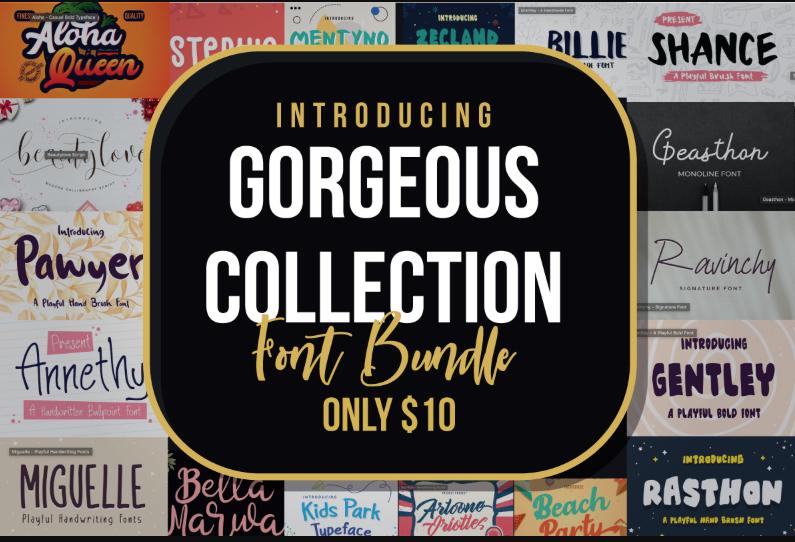
[Сreativefabrica] Gorgeous Collection Font Bundle (Ian Mikraz)
В этом пакете шрифтов вы получите 100 великолепных, профессиональных шрифтов ручной работы, идеально подходящих для всего, начиная от свадебных приглашений и заканчивая Apparel Brands и плакатами.
В этом великолепном пакете представлен широкий спектр стилей шрифтов: современная каллиграфия, монолитные шрифты, почерк сухой кистью, гранж, рустик, элегантные засечки, чистые засечки, акварельные, мультяшные, ужасы, стиль подписи, логотип и многое другое.